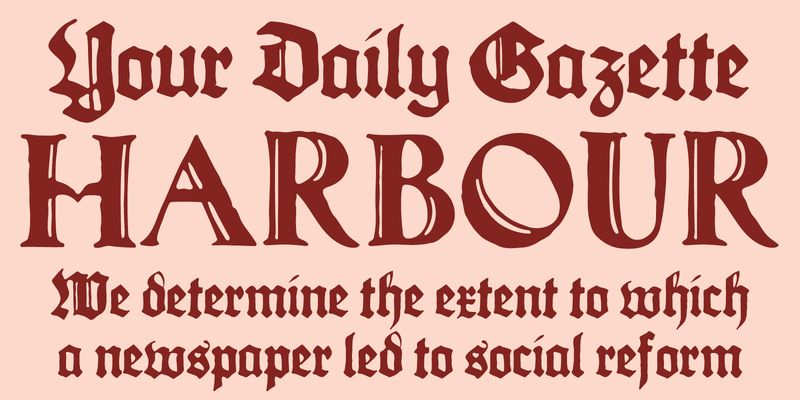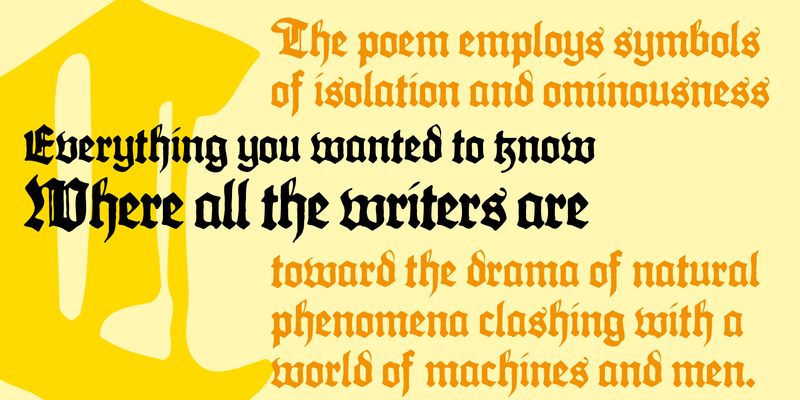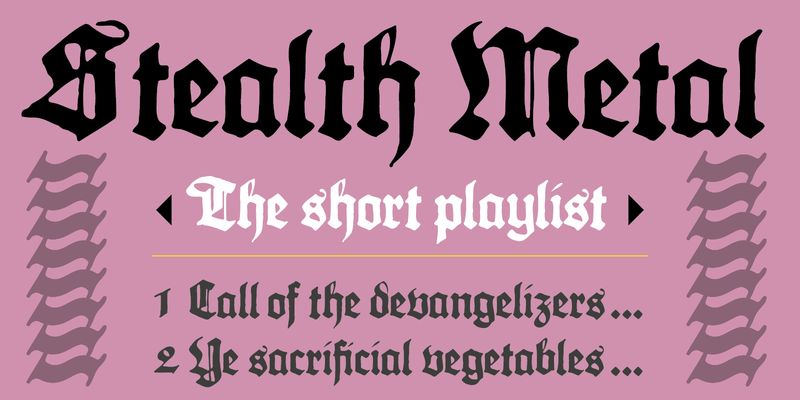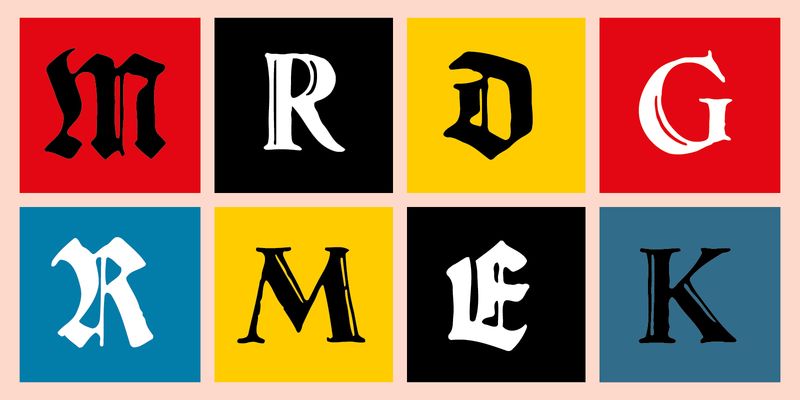
Aerotype wurde 1995 gegründet, um eine kleine Sammlung von Schriften zu beherbergen, die von Stephen Miggas erstellt wurden. Heute ist Aerotype vor allem für handgeschriebene Skripte wie Fave, Turbinado und Zooja, handsatzähnliche Digitalisierungen wie Thunderhouse mit seiner ursprünglichen Patina und andere handliche Display-Schriften bekannt.